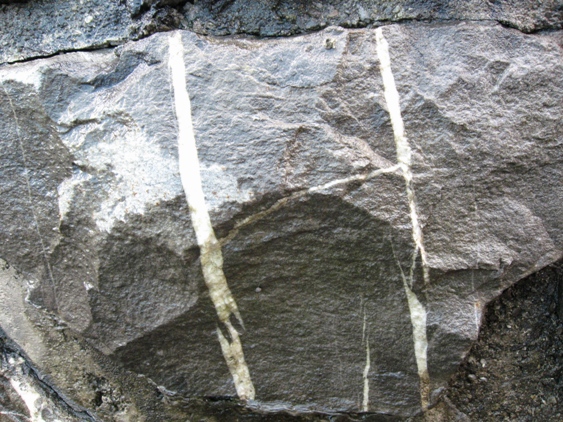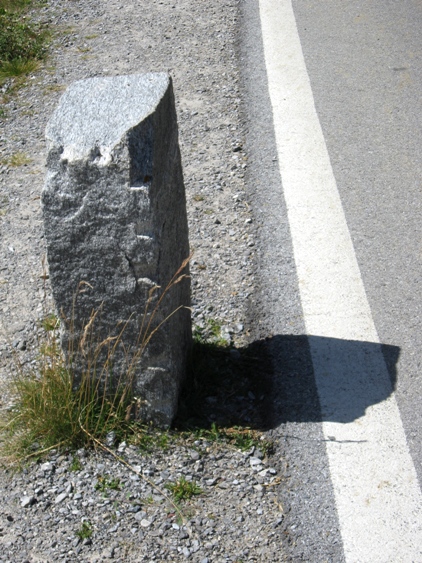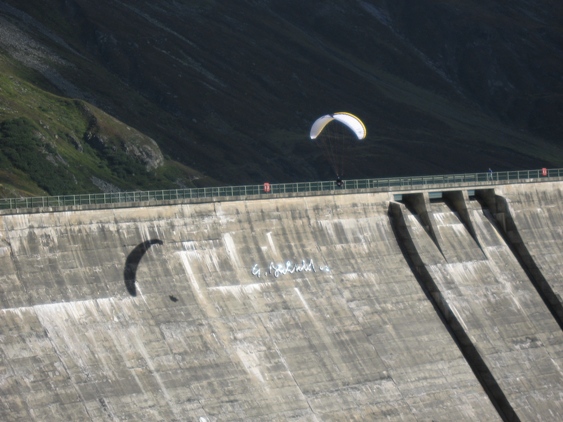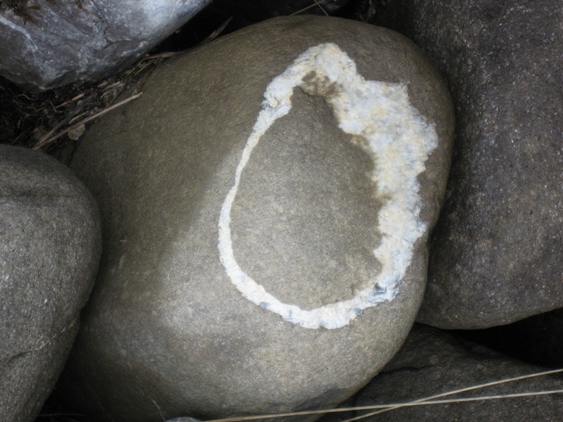
自然字アルファベット
さて・・・mojitor-fさんが故郷の美しい水辺に映る風景文字を報告・・・mojitor-sさんも
美しい手書き文字を報告・・・、と続きましたが・・・さてさて牛とか草の香りのする場所からは
どんな文字が現れたでしょうか〜??
ジ〜〜〜
ほほ〜光と影のコラボ(大げさですな)!飛んでるおじさんは危なっかしいですが、その影は「C」に見えました!クリックするともっと「C」
に見えるかも・・・です。
じ〜〜〜
これまた光と影が絶妙です(自画自賛ですな)!
Licht・ドイツ語では名詞は大文字から始まるので、まさしく
光の「L」に見えました!草の飾り付き?
(相方からイエローカードを出されそうな雰囲気・・・。)
さぁ・・・これらは、山や街で見かけた石たちが語る・・・「H」「O」「Y」ですね。「おおい」って
感じですか?
石はきれいですね・・・。色味にも変化があるし・・・何やら語る、語る・・・。
相方の・・・その目が「反則、反則・・・」って言ってるみたいなんですけど・・・。まぁ、まぁ、
自然の中の形ですから・・・。
おぉっ L かっこいいです、しかも植物の装飾つき!
Stone Alphabet も素敵ですね〜 やりますなぁ、自然。
本当は、最後にものすご〜くショボイ?「川」を
紹介する予定だったのに・・・忘れました(泣)。
いつかリベンジを!!(オチを忘れるなんて・・・)